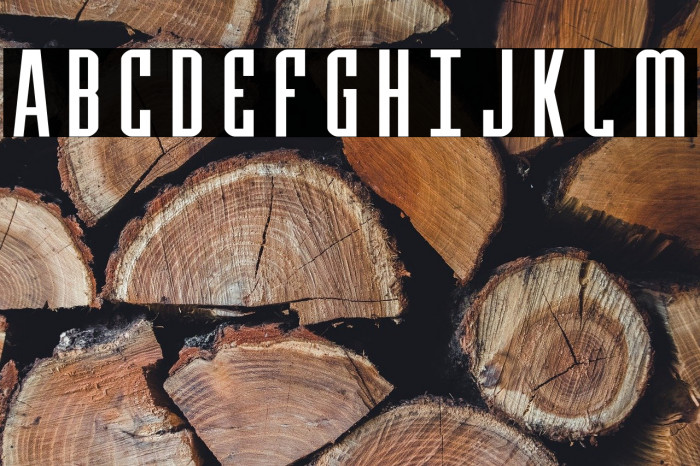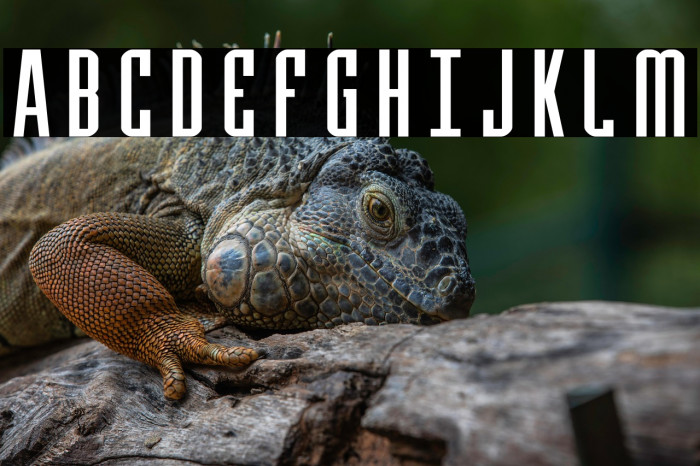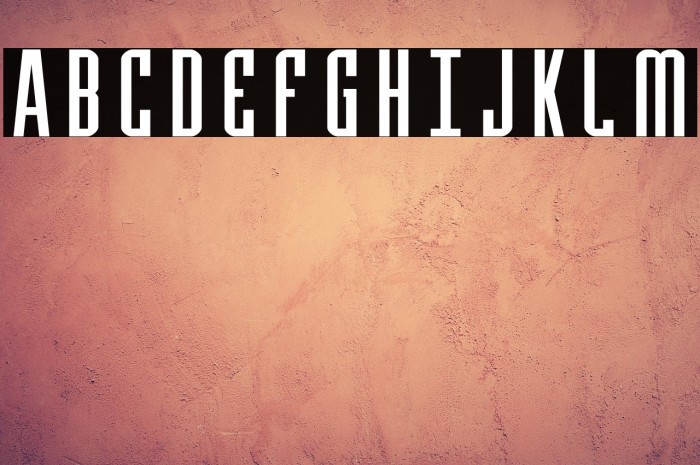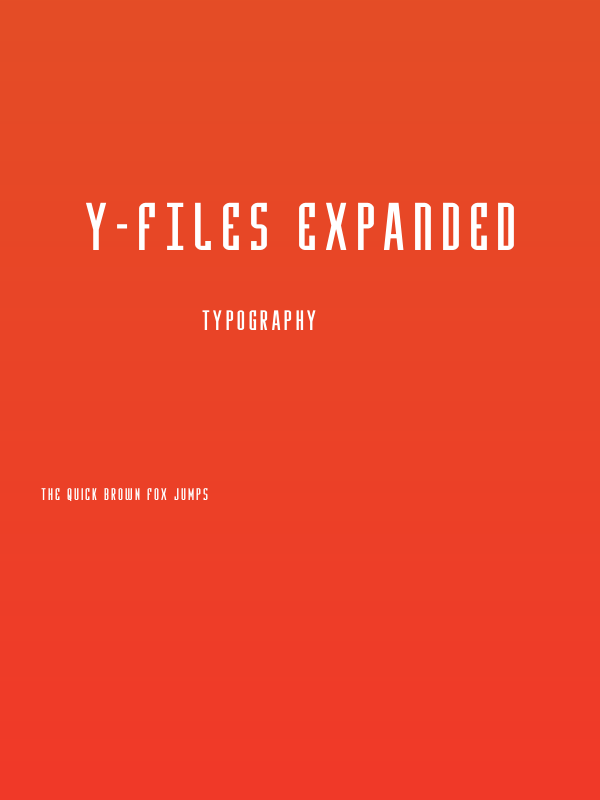
Y-Files Expanded Font
| Larghezza | Expanded |
| Progetti proposti | Ideal for headlines, posters, branding, and any design requiring a strong, impactful typeface. |